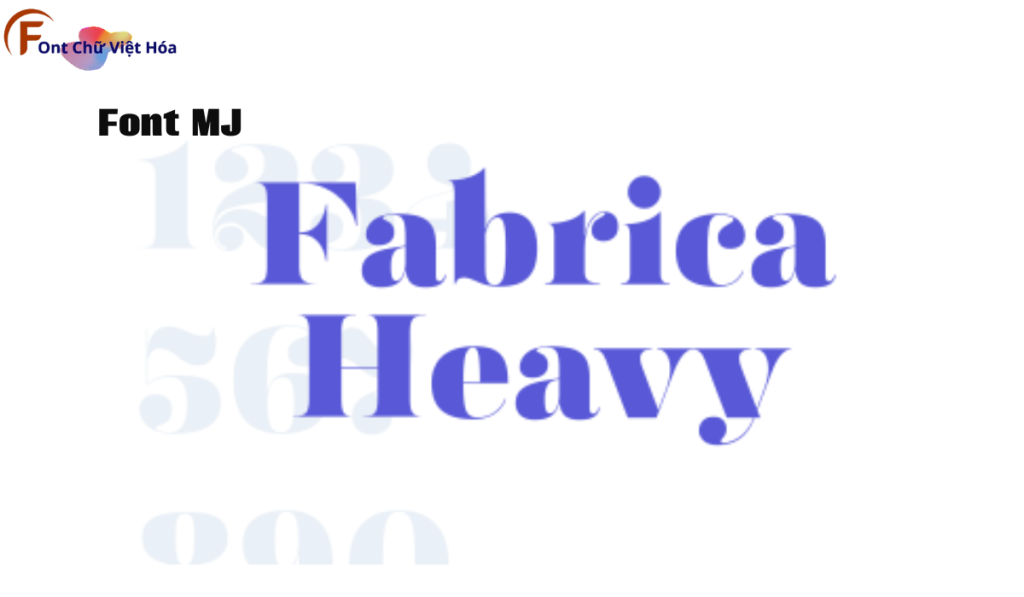
Font MJ Fabrica – Heavy Việt Hóa
Font MJ Fabrica-Heavy Việt Hóa
Tác giả: MJ Type
Bộ Font: MJ
Phân loại: Cá tính, Độc đáo
Độ dày: Heavy
Font MJ Fabrica-Heavy Việt Hóa là một font chữ không chân mạnh mẽ, thuộc bộ font MJ. Được thiết kế với mục tiêu mang lại sự nổi bật và ấn tượng, font này lý tưởng cho các dự án thiết kế như tiêu đề, quảng cáo, và bao bì sản phẩm. Với các nét chữ đậm và chắc chắn, Font MJ Fabrica-Heavy Việt Hóa không chỉ dễ đọc mà còn tạo cảm giác mạnh mẽ và quyết đoán. Việc Việt hóa font giúp người dùng dễ dàng sử dụng trong các thiết kế tiếng Việt, mang lại sự tiện lợi và thẩm mỹ cao.